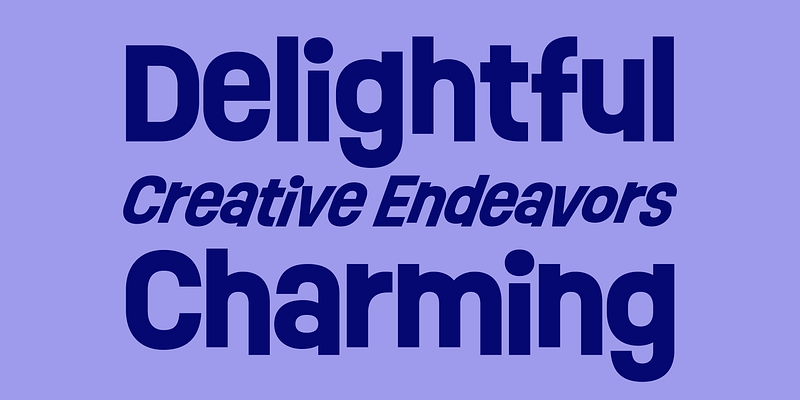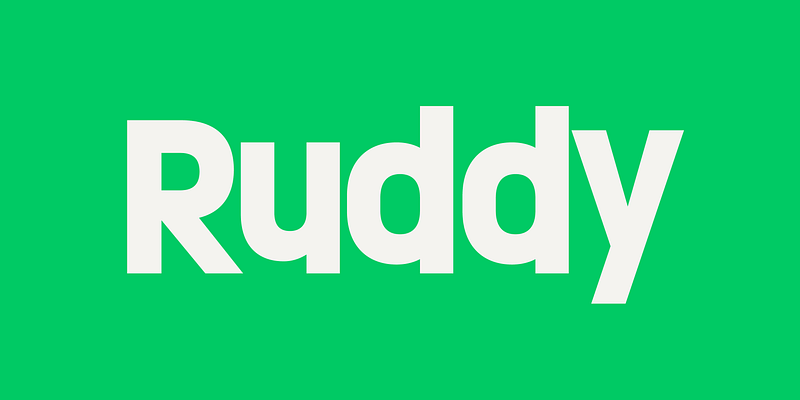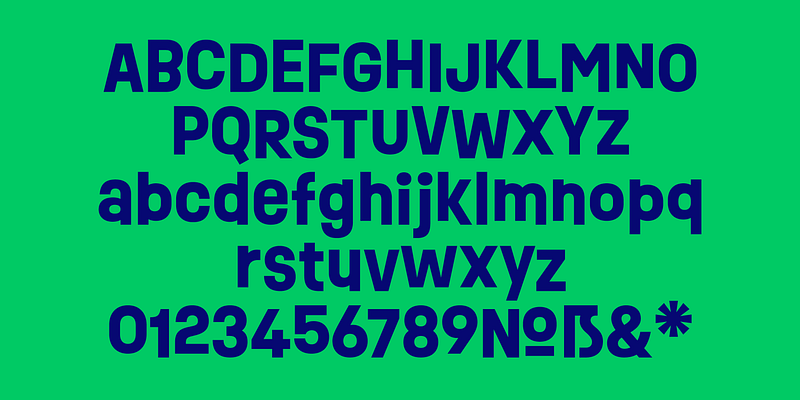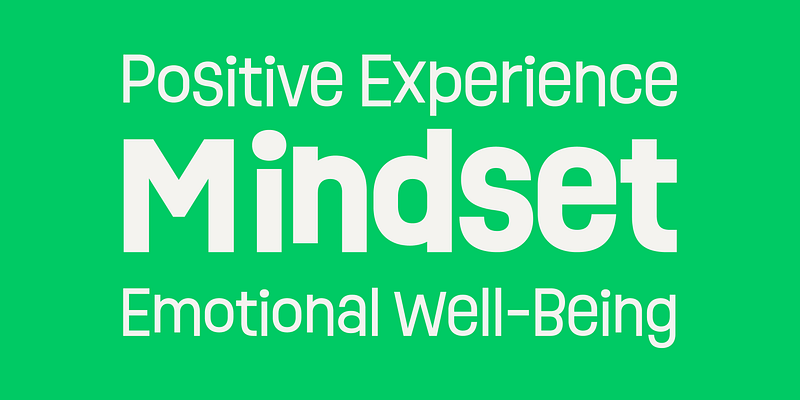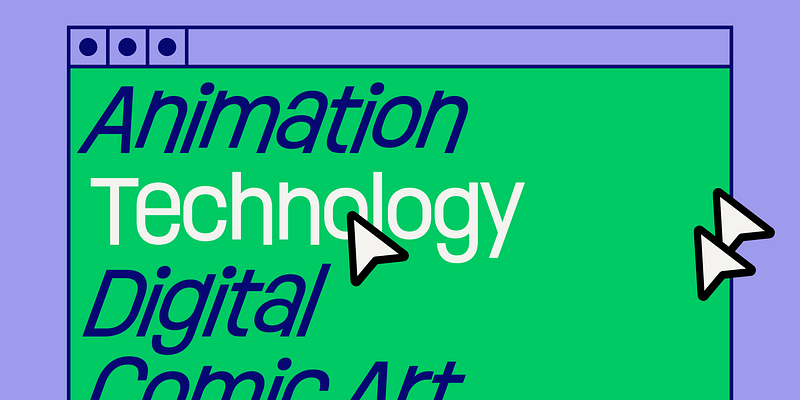
Ruddy es una familia tipográfica de palo seco para pantalla. Tiene una presencia juguetona y traviesa. La geometría exagerada y la variada ubicación del asta vertical de los caracteres contribuyen a su aspecto animado. Ruddy viene en 4 pesos con bastardilla a juego. Las características de OpenType incluyen alternativas contextuales, figuras tabulares, fracciones, numeradores y denominadores.